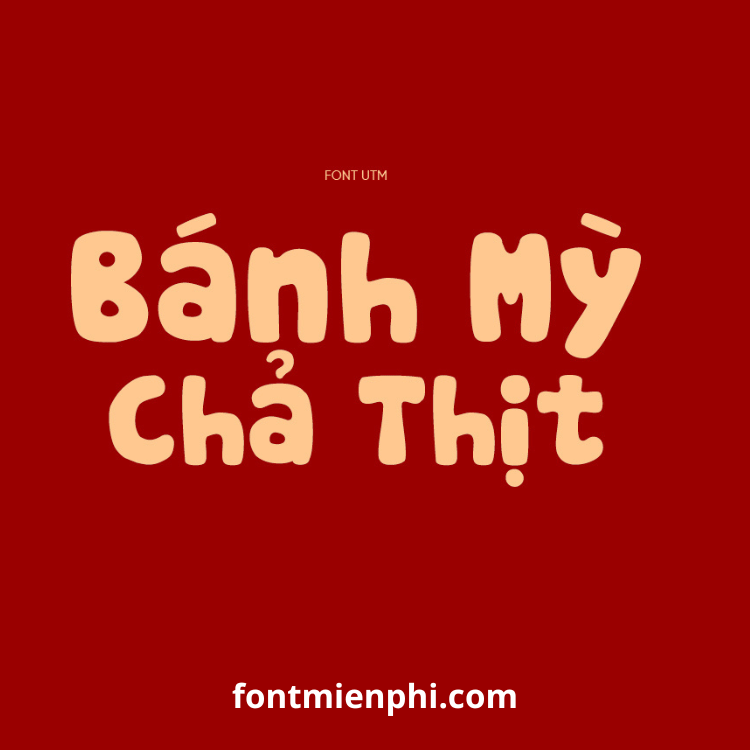
Việt hóa font UTM Cookies
Mô Tả Chi Tiết Font Việt Hóa “UTM Cookies”
1. Giới Thiệu Chung
UTM Cookies là font chữ viết tay (handwriting) đáng yêu với nét chữ tròn trịa, mềm mại như những chiếc bánh cookie ngọt ngào. Font mang phong cách ấm áp, thân thiện, cực kỳ phù hợp cho các thiết kế liên quan đến ẩm thực, đồ ngọt, quà tặng, thiệp mời và các sản phẩm hướng đến đối tượng trẻ em hoặc phái nữ.
2. Đặc Điểm Nổi Bật
✔ Phong cách handwriting ngọt ngào: Nét chữ tròn, mềm mại tự nhiên như viết tay
✔ Hỗ trợ đầy đủ Tiếng Việt: Bao gồm đầy đủ dấu và ký tự Unicode chuẩn
✔ Đa dạng ký tự: Gồm chữ hoa, chữ thường, số và ký tự đặc biệt cơ bản
✔ Dễ sử dụng: Phù hợp cho cả digital lẫn in ấn với độ rõ ràng cao
3. Ứng Dụng Chính
• Thiết kế bao bì bánh kẹo, thực phẩm
• Menu quán café, tiệm bánh
• Thiệp sinh nhật, thiệp mời
• Nội dung quảng cáo mỹ phẩm, đồ trẻ em
• Blog ẩm thực, sổ tay công thức
Pro Tip: Kết hợp UTM Cookies với màu pastel và hình minh họa đồ ngọt sẽ cho hiệu quả thiết kế tuyệt vời! ✨